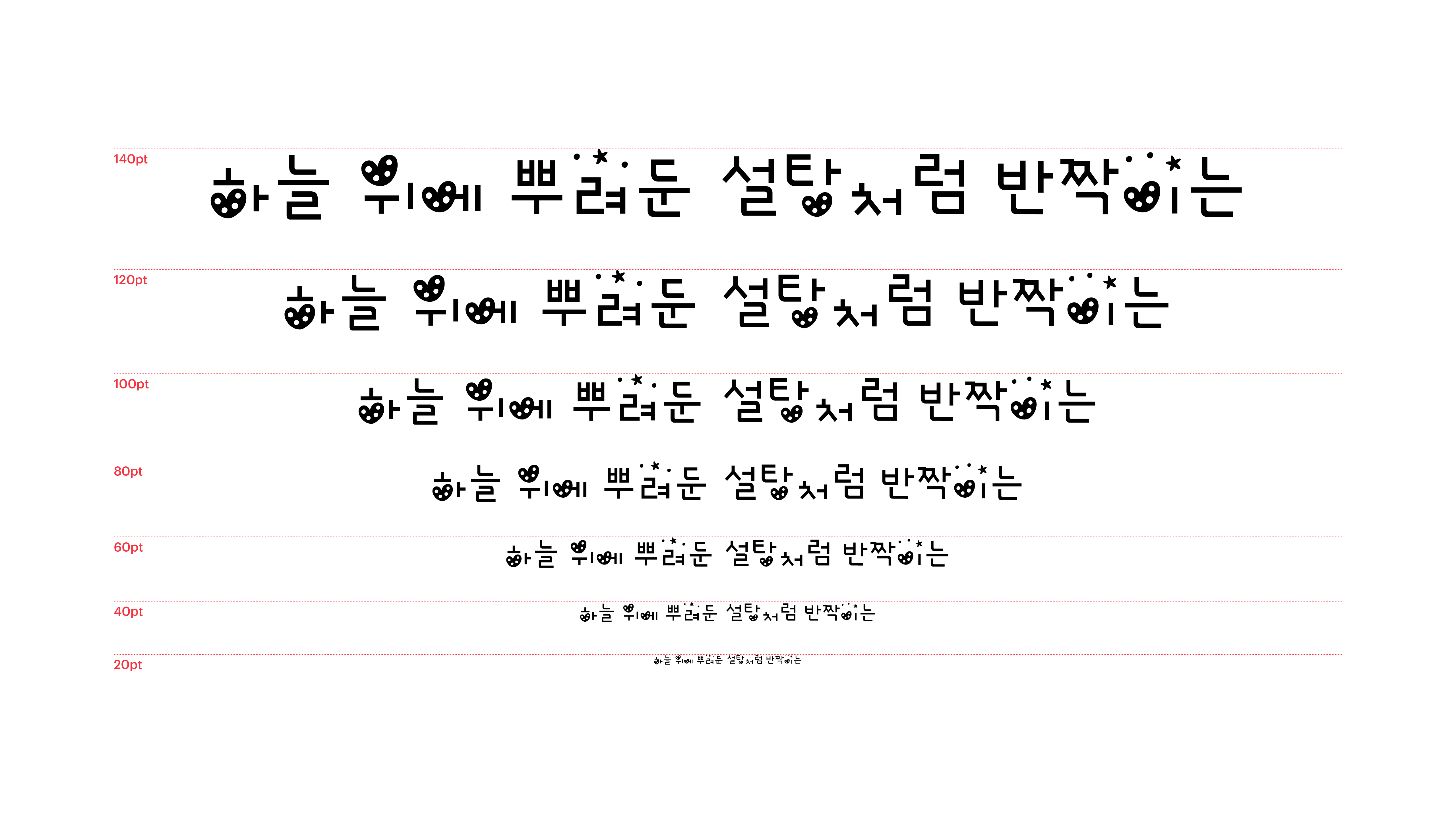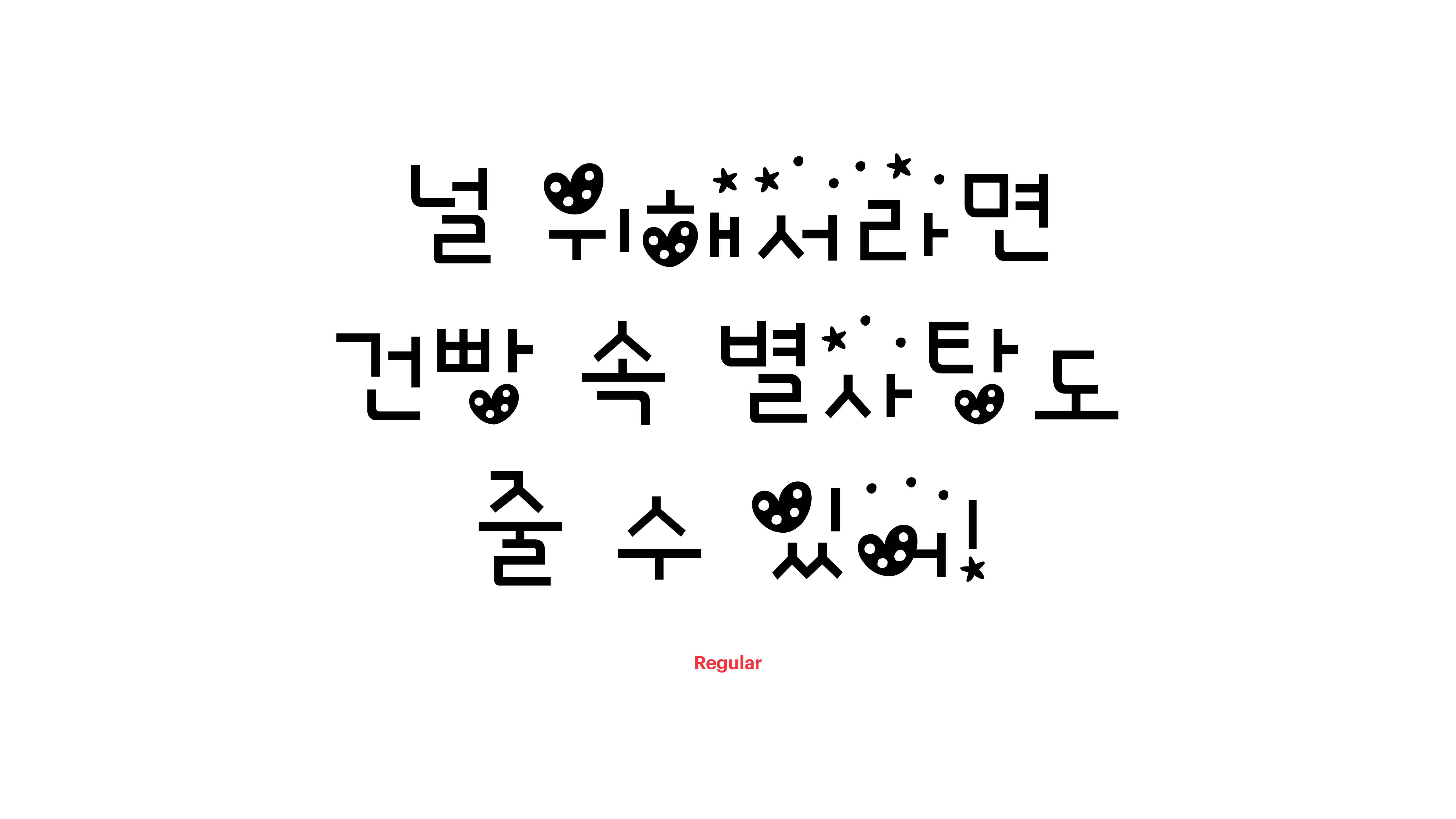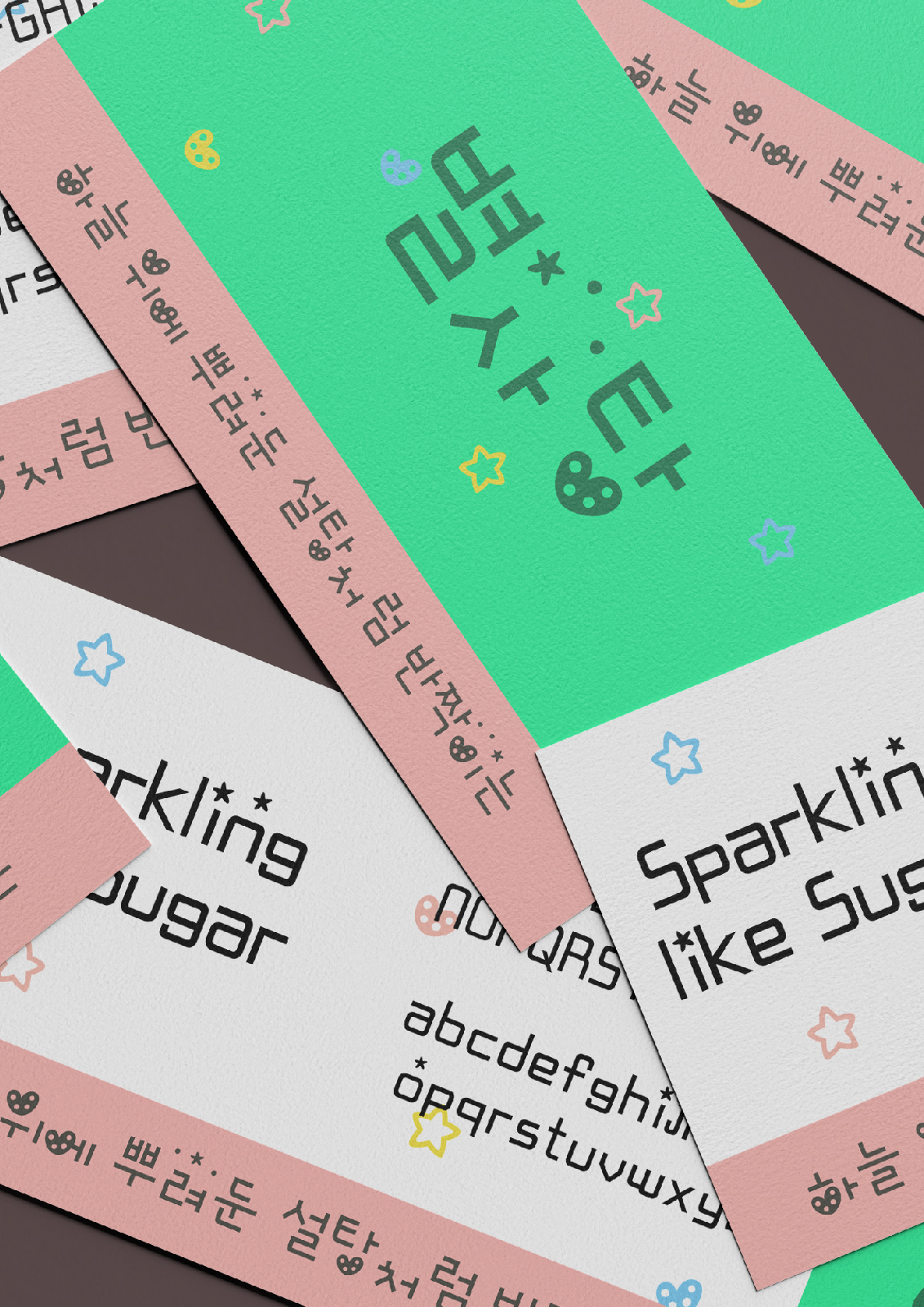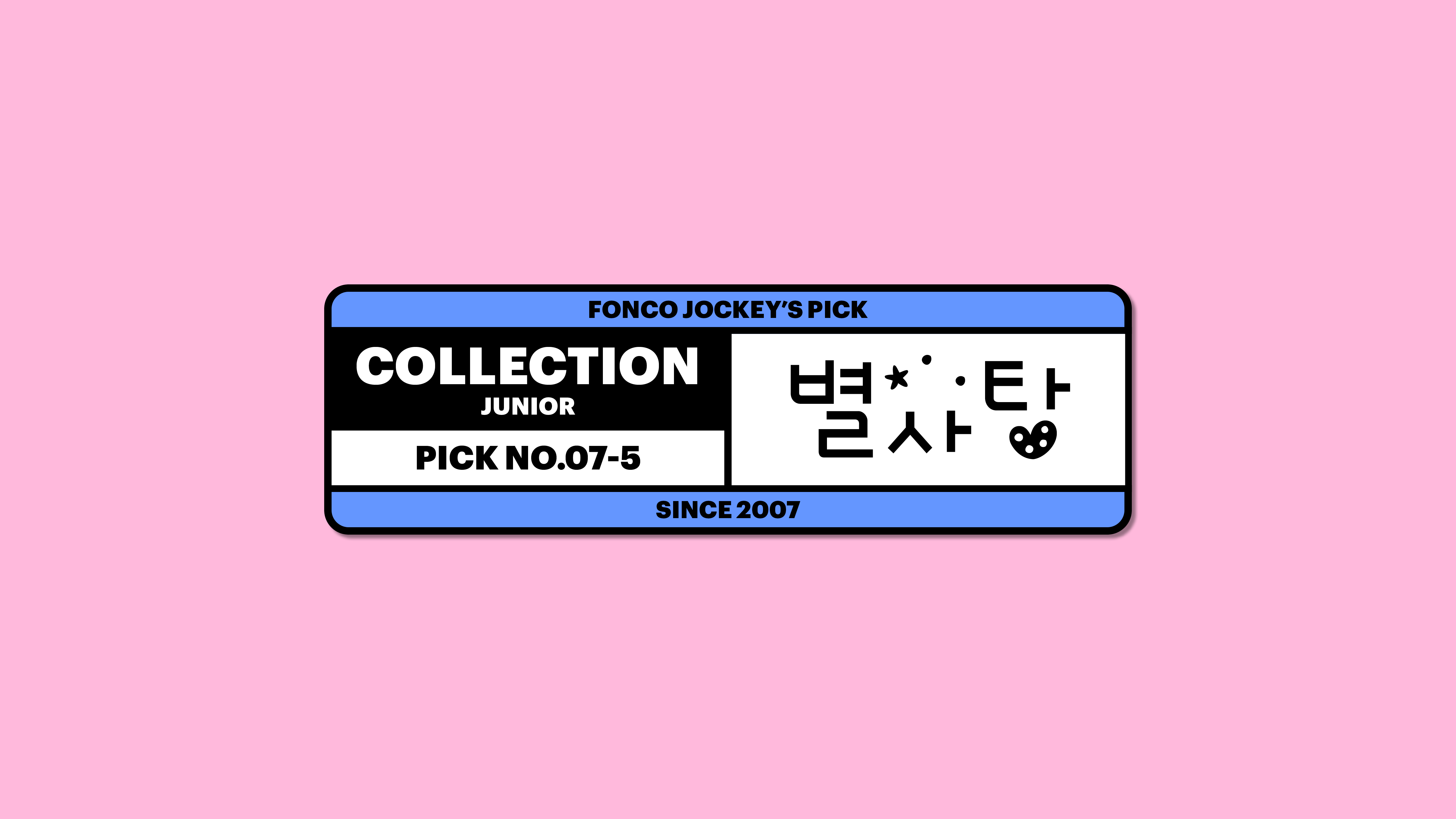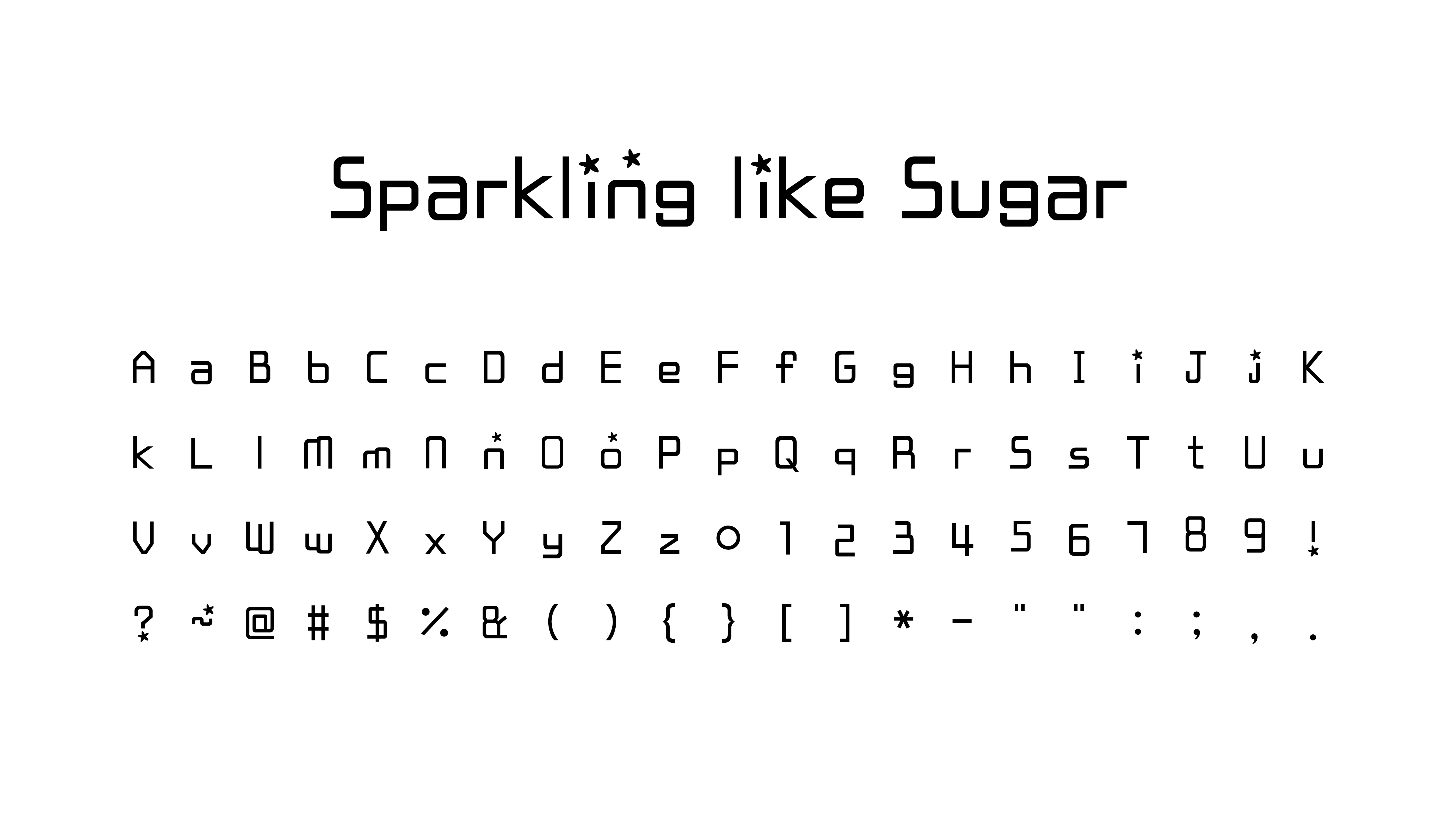
별사탕
Yoon 별사탕
별무리를 알고 계시나요? 하늘 위에 뿌려둔 설탕처럼 황홀하고 반짝이는 별무리의 이미지를 폰트 안으로 쏙 옮겨봤어요. 그러니 이 달콤한 폰트로는 아무 검열 하지 말고, 하고 싶은 말을 다 적어보시겠어요? 어떤 이야기를 적어도 반짝이게 만드는 능력으로 여러분의 이야기를 꼭 감싸볼게요.